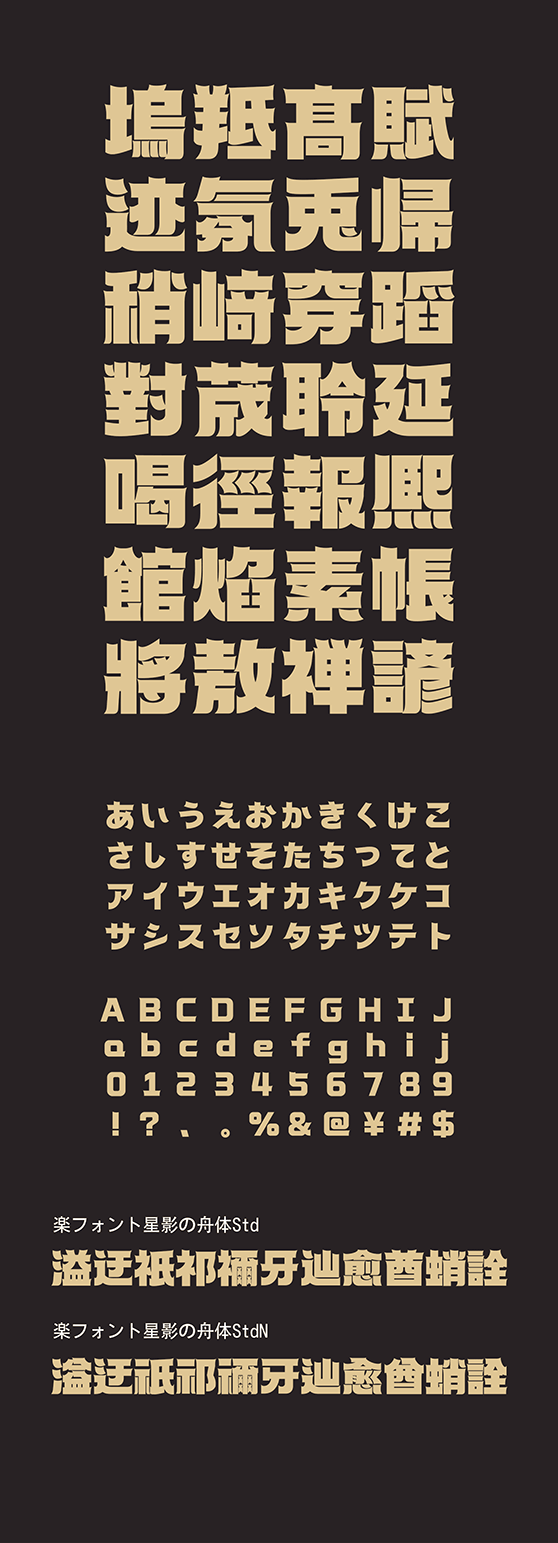
楽フォント
星影の舟体 (ほしかげのふねたい Std・StdN同梱)
HoshikagenofunetaiStd, HoshikagenofunetaiStdN
極太の筆画とやわらかなコーナーにより、力強さと親しみやすさをあわせ持つフォントです。ふくらみのある字形が存在感を生み、丸み処理がさをやわらげて読みやすさを高めます。タイトルやパッケージ、サイン、広告など、明快なインパクトと信頼感を伝えたい場面に最適です。